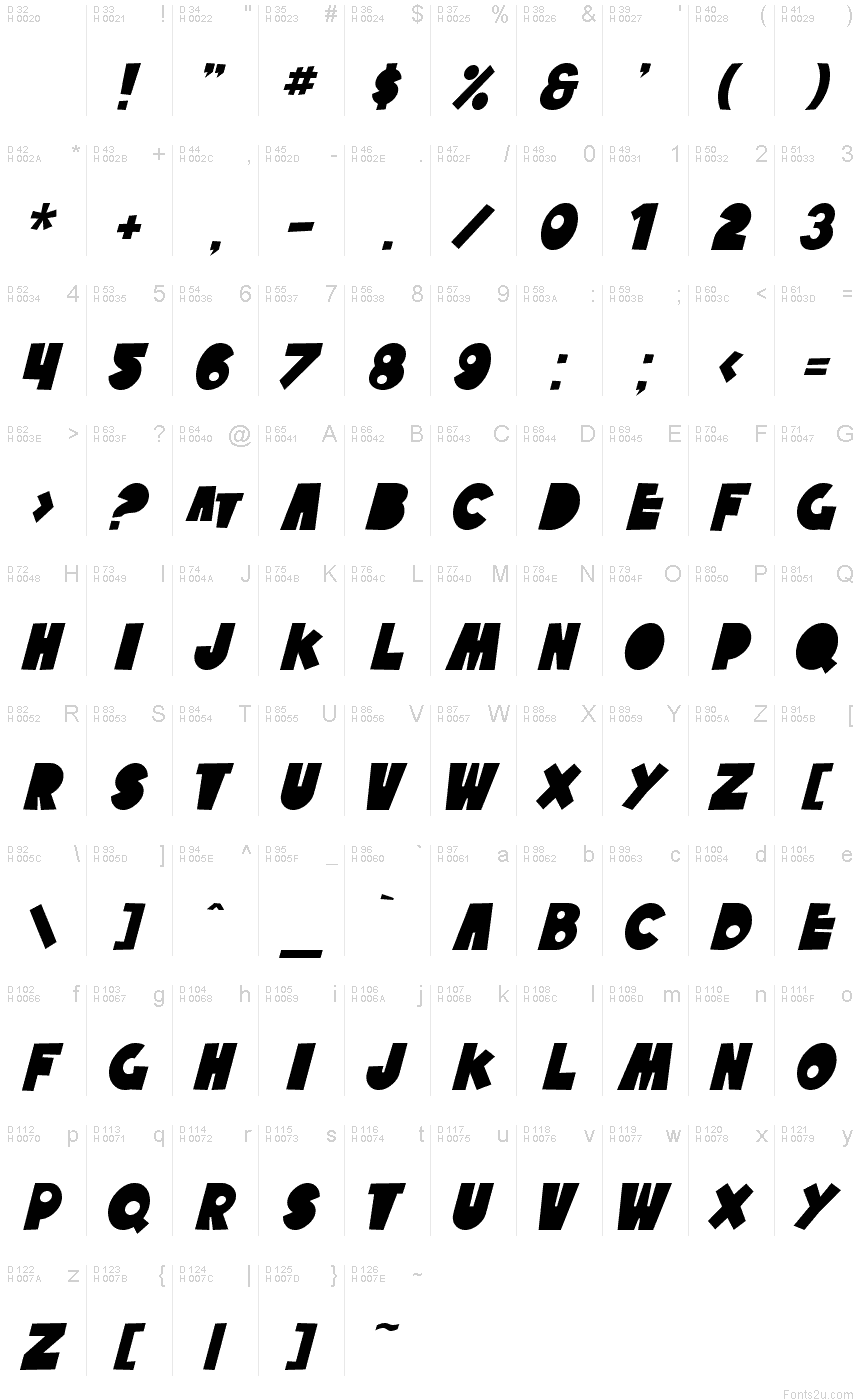
SF Tattle Tales Italic von ShyFoundry ist eine kostenlose Comic-Display-Schrift mit großen, kursiven Großbuchstaben, die laut, schnell und ein wenig schelmisch wirken. Die Buchstaben sind wie klobige, schwarze Formen mit scharfen Ecken und übertriebenen Winkeln gestaltet, was dem Alphabet eher einen Comic-Stil verleiht als glatte Retro-Eleganz.
Sie passt perfekt zu Postern, Kinderbüchern, Party-Flyern, Spieletiteln und auffälligen Verpackungen, bei denen ein paar Worte einen verspielten Akzent brauchen. Als Gratis-Font eignet sie sich zudem hervorragend für knallige Schlagzeilen, Monogramme und kurze Logo-Skizzen, da der kräftige Kursiv-Rhythmus selbst einfachen Wörtern eine dynamische Energie verleiht.